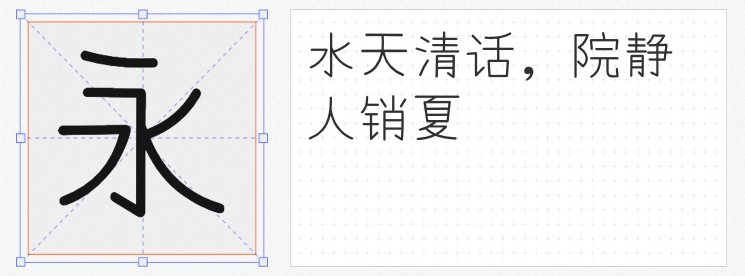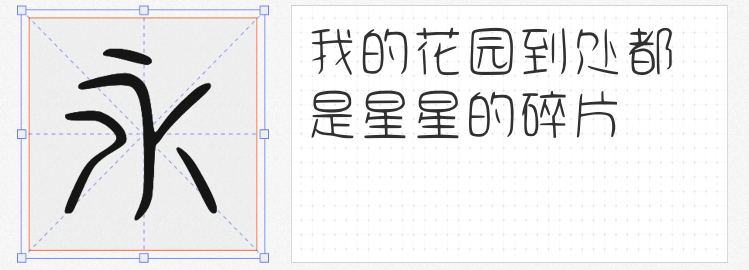
在数字化设计浪潮中,手写字体以其独特的温度感和灵动性,成为品牌传递清新气质的关键元素。以下四款免费商用字体,以自然流畅的笔触和多元风格表现,为海报、包装、广告等场景注入鲜活生命力,让设计兼具美学价值与实用价值。
这款字体以“无棱角设计”为核心,笔画如被春风抚过般柔和。横竖转折处采用大弧度圆角处理,起笔收笔自然衔接,形成棉花糖般的视觉质感。其适中的字间距与行间距设计,使长文本排版时既能保持呼吸感,又不会显得松散。无论是母婴产品包装上的短句标语,还是文艺海报中的主视觉文案,都能通过这种温润的笔触传递出治愈感,尤其适合需要营造舒适氛围的消费场景。
基于Yomogi字体优化而来的有梦体,在保留日式手写体轻盈特质的同时,针对简体中文使用习惯进行深度改造。设计师通过调整“讠”“钅”等偏旁的结构比例,使字体更符合大陆用户的阅读习惯;对风格差异较大的汉字进行翻新设计,确保整体视觉统一。笔画起收处的毛边处理模拟真实书写痕迹,而0.8倍字高的x高度设计,则让中英文混排时保持平衡,成为文创产品标签、手账模板设计的理想选择。
云峰字库出品的这款字体,以“教科书级规范书写”为目标。每个笔画的起笔、行笔、收笔都遵循严格的书法规范,横平竖直中暗含提按变化,撇捺舒展却不过度夸张。其规整的字形框架确保了远距离识别的清晰度,而手工书写的细微抖动又保留了真实感。这种“严谨中的灵动”特质,使其成为教育类书籍封面、传统工艺品牌视觉系统的优质解决方案。
收录近9000个汉字的可爱手写体,以“习惯性的手写风格”为特色。日式简化的汉字结构与中文传统写法巧妙融合,如“门”字框的圆弧处理既保留手写温度,又确保了简体字的识别度。丰富的字符集支持从社交媒体文案到长篇书籍排版的全方位需求,而笔画中特有的连笔习惯与个性笔锋,则为设计师提供了自由创作的空间。
四款字体分别从温润、融合、工整、多元等维度切入,通过免费商用的开放属性,打破了手写风格设计的成本壁垒。设计师可根据品牌调性选择适配字体,在保持视觉新鲜感的同时传递真挚情感,让每一次笔触都成为连接用户情感的桥梁。